Font Việt Hóa Viết Tay Cho Thiệp Mời & Sự Kiện Đẹp Mắt
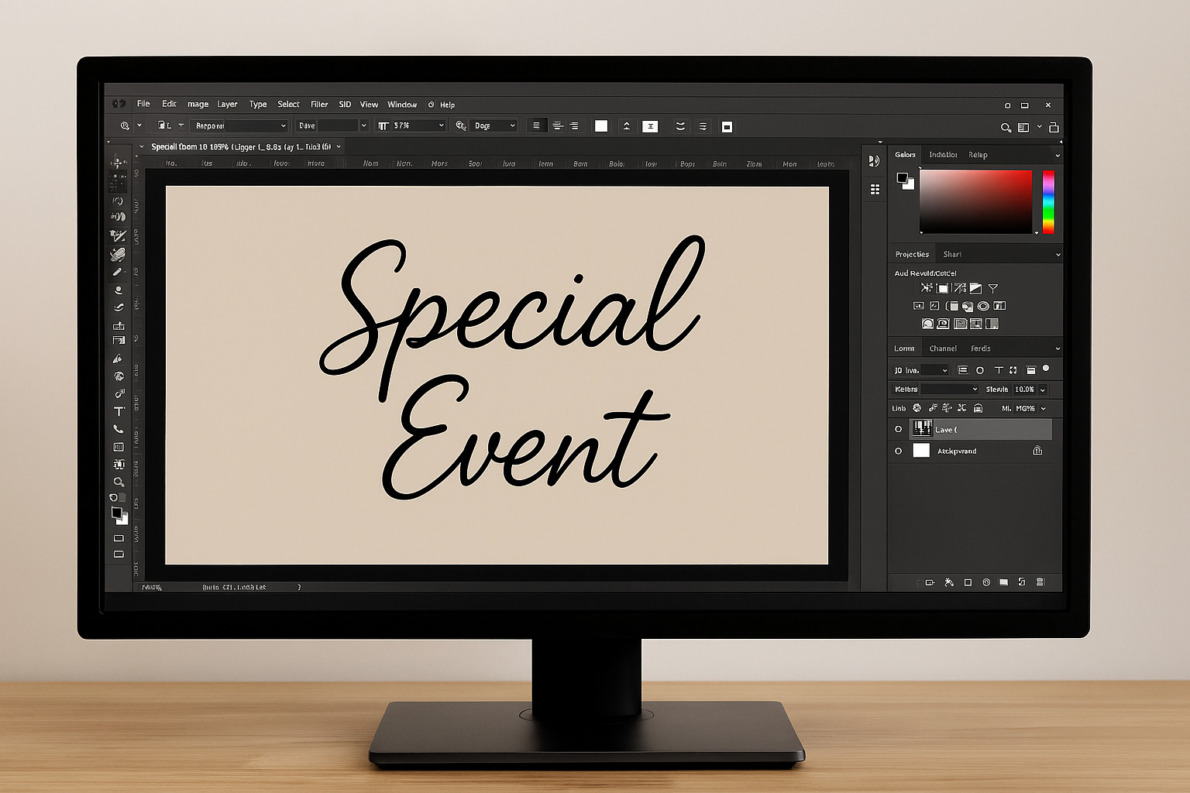
Khi thiết kế thiệp mời cưới, thiệp sinh nhật, hoặc các ấn phẩm sự kiện cá nhân, font chữ đóng vai trò quan trọng không kém nội dung. Một font Việt hóa viết tay đẹp, đúng dấu, mềm mại sẽ giúp thiệp của bạn trở nên ấm áp, chân thành và mang đậm dấu ấn cá nhân.
Font Việt Hóa Viết Tay Là Gì?
Đây là những phong chữ viết tay nước ngoài đã được Việt hóa, nghĩa là đã được chỉnh sửa để hiển thị đầy đủ dấu tiếng Việt, nhưng vẫn giữ được nét mềm mại, nghệ thuật của kiểu viết tay gốc.
Font này thường mô phỏng nét bút máy, chữ tay hoặc thư pháp – rất phù hợp cho các thiết kế mang tính cảm xúc, cá nhân hóa cao.
Vì Sao Nên Dùng Font Việt Hóa Viết Tay Cho Thiệp Mời?
Hiển thị đúng tiếng Việt – tránh lỗi sai dấu, mất ký tự
Tăng tính thẩm mỹ & cảm xúc cho thiệp mời
Độc đáo, riêng biệt, không cứng nhắc như font hệ thống
Tạo phong cách nhẹ nhàng, sang trọng hoặc cổ điển tùy chọn font
Một Số Font Việt Hóa Viết Tay Gợi Ý
| Tên Font | Phong cách | Phù hợp với |
|---|---|---|
| iCiel Cadena Script | Lãng mạn, nghệ thuật | Thiệp cưới, thư tay |
| UVN Bay Buom | Trẻ trung, mềm mại | Thiệp sinh nhật |
| Lora Việt Hóa | Cổ điển, thanh lịch | Thiệp sự kiện trang trọng |
| iCiel BrushUp | Mạnh mẽ, tự nhiên | Poster sự kiện cá nhân |
Tất cả các font trên đều đã Việt hóa và hỗ trợ đầy đủ dấu.
Cách Dùng Phong Việt Hóa Viết Tay Hiệu Quả
Sử dụng font viết tay cho tiêu đề chính hoặc tên người nhận
Kết hợp với font sans-serif để dễ đọc phần nội dung
Giữ khoảng cách chữ hợp lý để tránh rối mắt
Kết Luận
Font Việt hóa là lựa chọn tuyệt vời để thể hiện sự tinh tế và cá tính trong các thiết kế thiệp mời & ấn phẩm sự kiện. Không chỉ đẹp về hình thức, những kiểu chữ này còn giúp bạn truyền tải cảm xúc chân thành qua từng dòng chữ.